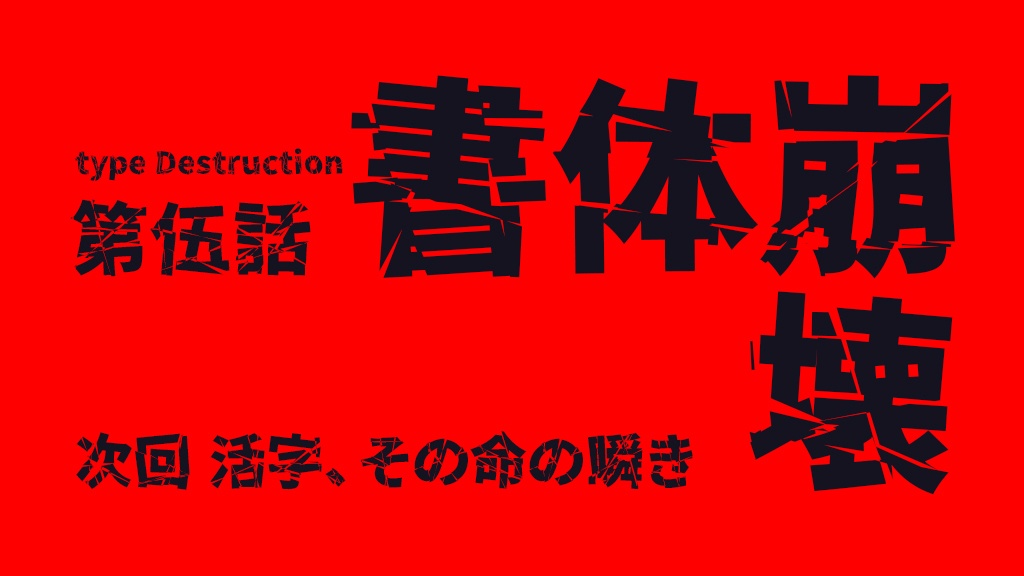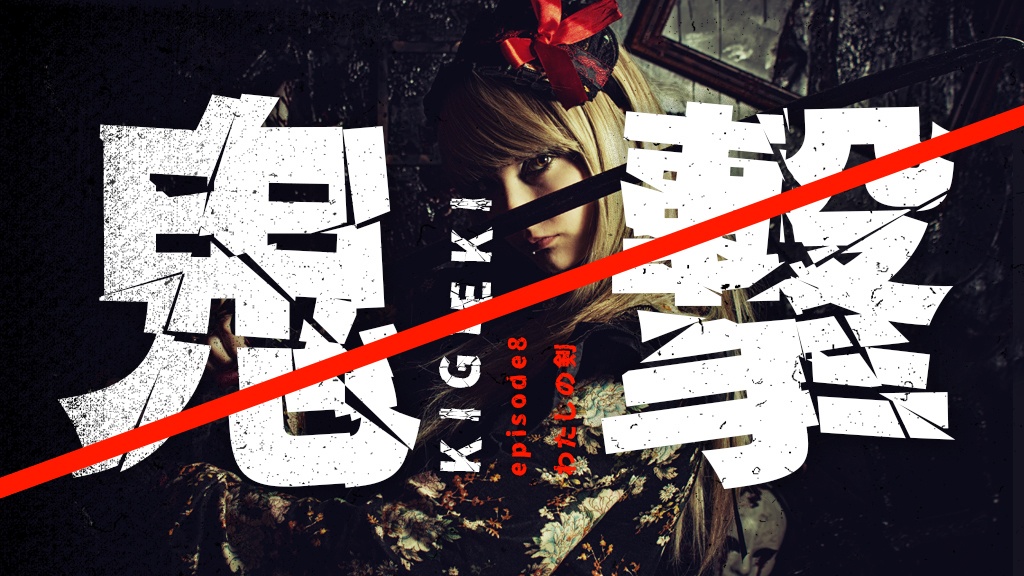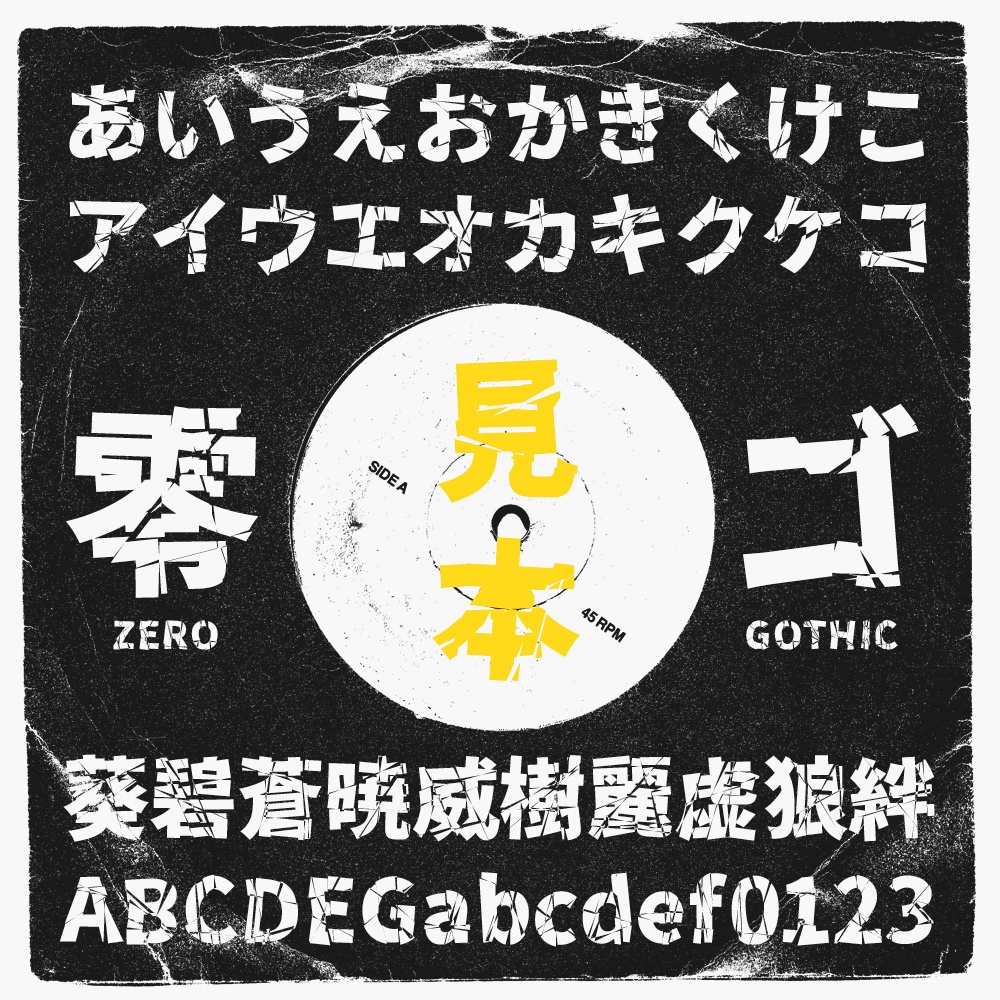
零ゴシック(フリーフォント)
零ゴシック【ゼロゴシック】は、文字が割れているインパクトのあるフォントです。見出し・ロゴにピッタリのデザイン。 文字数は8000字以上揃っていますので、安心してお使い頂けます。 ■フリーフォント使用に当たって フォントをインストールして頂くとパソコンのワープロ、グラフィックソフトなどのアプリケーションを使って自由にデザイン、印刷することができます。個人利用・商用利用にかかわらず、無償で使用することができます。当フォントはSIL Open Font License 1.1のオープンソースライセンスに準じます。 ■零ゴシックの概要 零ゴシックは「源ノ角ゴシック」のフォントを改変して制作した派生フォントです。 制作に関わる全ての方に深くお礼申し上げます。 当フォントはFontlabStudio、武蔵システム(http://opentype.jp/)OTEditで作成しました※フリーフォントのインストール・ソフトでの使用についてのサポート・お問い合せは受け付けません。 ⚠️このフォントは自由に動画に使えるフォントです。ご利用の際は次のクレジットを入れていただけると、ものすご〜く喜びます! –––––––––––––––––––––––––––––– フォント:零ゴシック フリーダウンロード:https://flopdesign.booth.pm/items/2658538 –––––––––––––––––––––––––––––– お好きなSNSをフォローしてください。 Instagram ▶ https://www.instagram.com/flopdesign.font X ▶ https://twitter.com/flopdesign Threads ▶ https://www.threads.net/@flopdesign.font